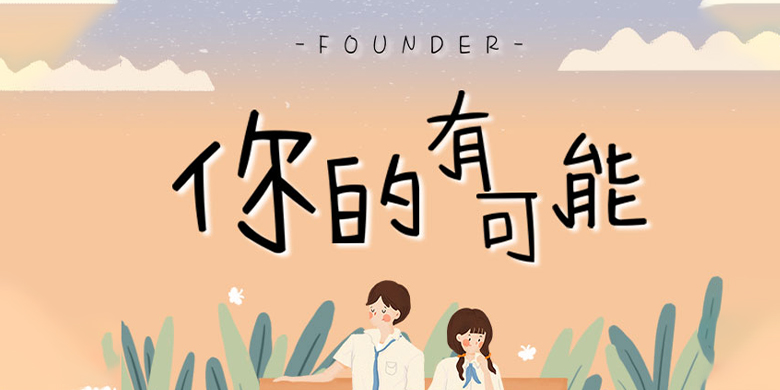
方正手迹-你的有可能
字体品牌: 方正手迹 设计师:刘晔 字体分类:创意书写 字体属性:精品字 字符集:大陆简体(GB2312-80) 发布时间: 2019
该款字体风格明显,字体大多有左倾趋势,部件转角处理多用尖角,部分笔画的采用勾的形式收笔,体现了该字富有青春朝气、积极进取的气质特点。适用于少儿类书刊,及现代诗歌、短文的排版以及文化、商业类品牌的广告语设计。